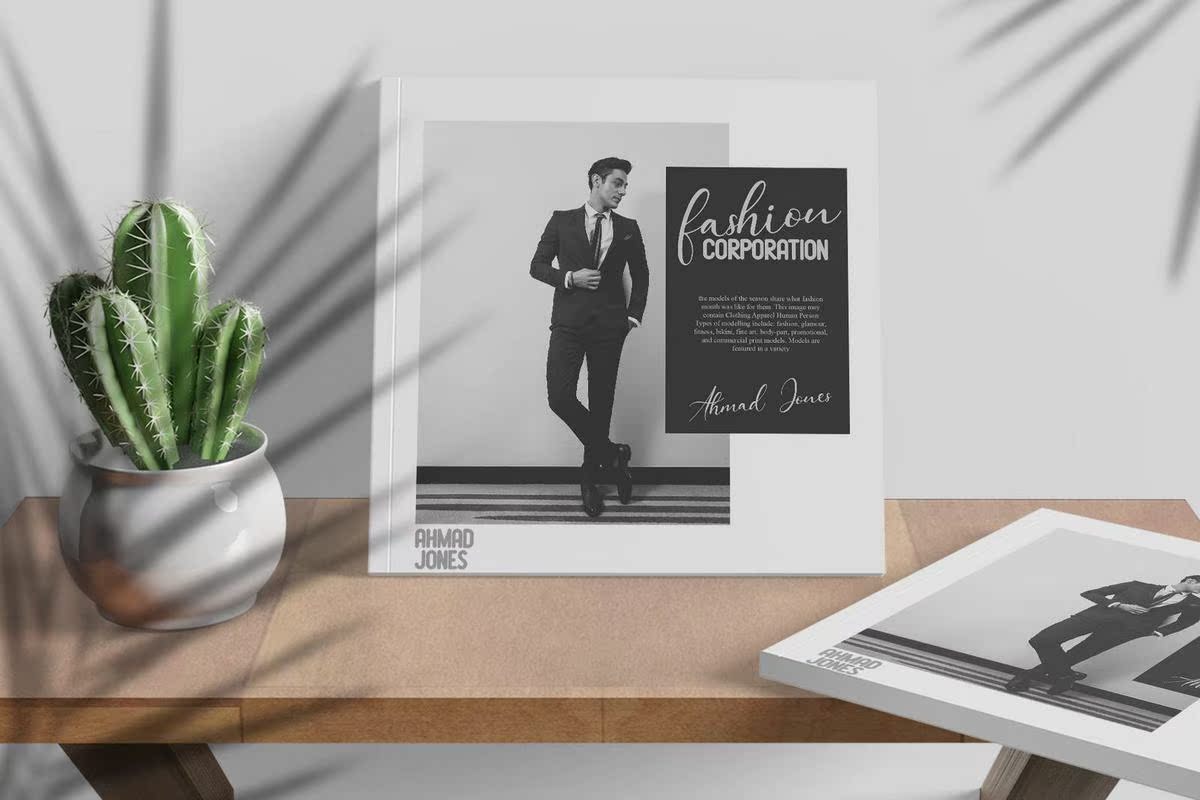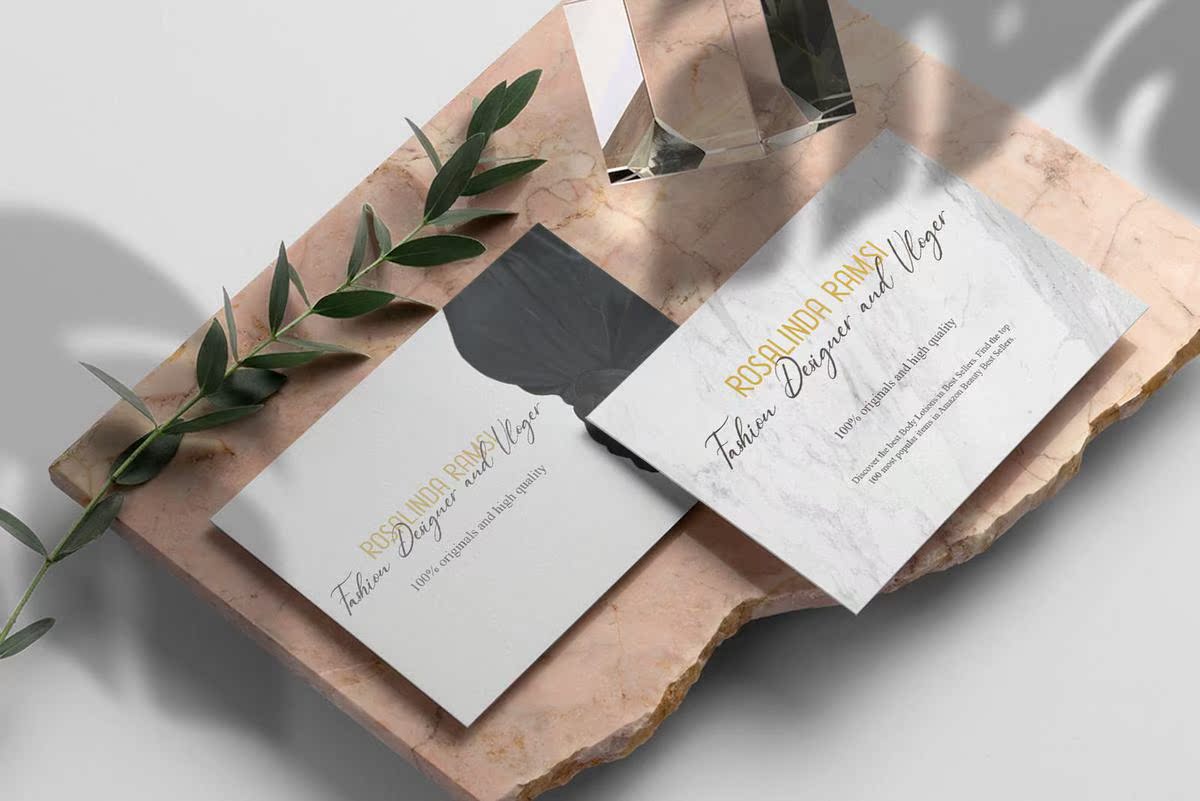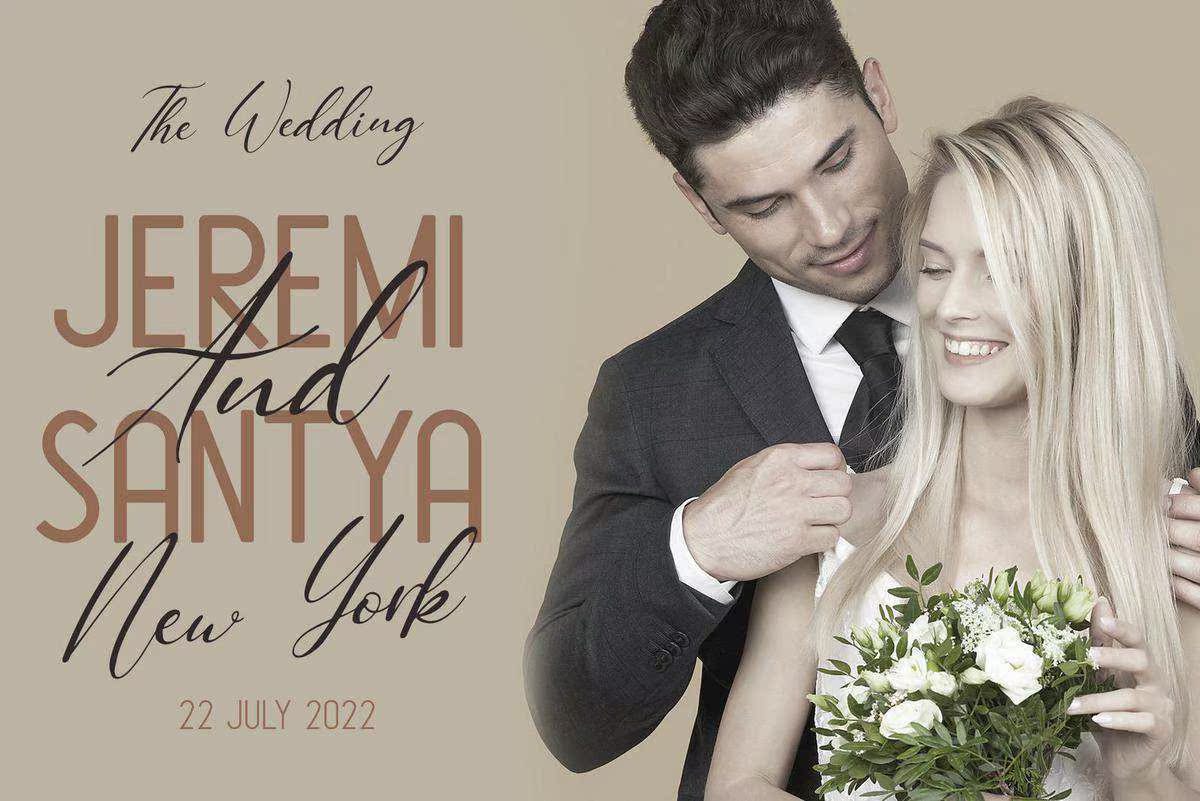
QueensignatorFontDuo,Display&ScriptTypefont。适合您的项目的文字和数字集合非常适合于标识、品牌设计、标识设计、数字字母艺术、T恤/服装、海报、杂志、标志、广告设计和任何设计需求。QueensignatorFontDuo,Display&ScriptType字体。适合您的项目的文字和数字集合非常适合于标识、品牌设计、标识设计、数字文字艺术、T恤/服装、海报、杂志、标志、广告设计和任何设计需求。